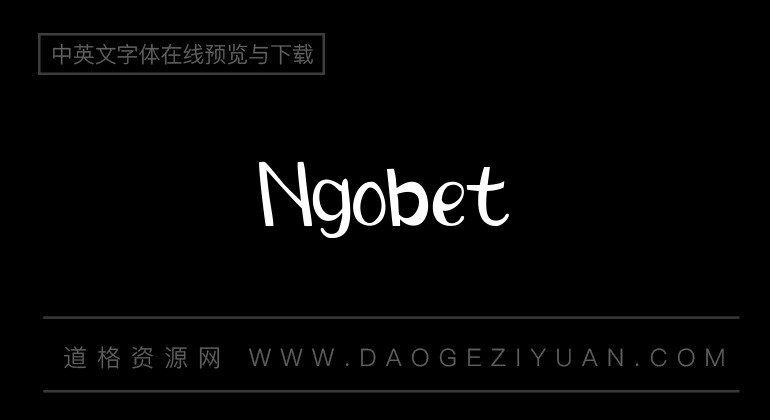
Ngobet
Ngobet 字体是一款拥有清新可爱风格的无衬线字体,它的字体风格灵感来源于印尼传统的艺术风格,以及传统的绘画和装饰元素。Ngobet 字体具有轻松、有趣的特质,可以为您的设计提供非常独特的视觉效果。它具有简洁、清爽的外观,可以让您的设计更加精致。此外,Ngobet 字体还具有支持多种语言的功能,可以满足不同语言的使用需求。
Ngobet是一款非常不错的手写艺术字体,具有很好的视觉感,适合于文化类的宣传设计、商业类品牌的广告和产品包装设计以及个性化文字排版等较多场景。